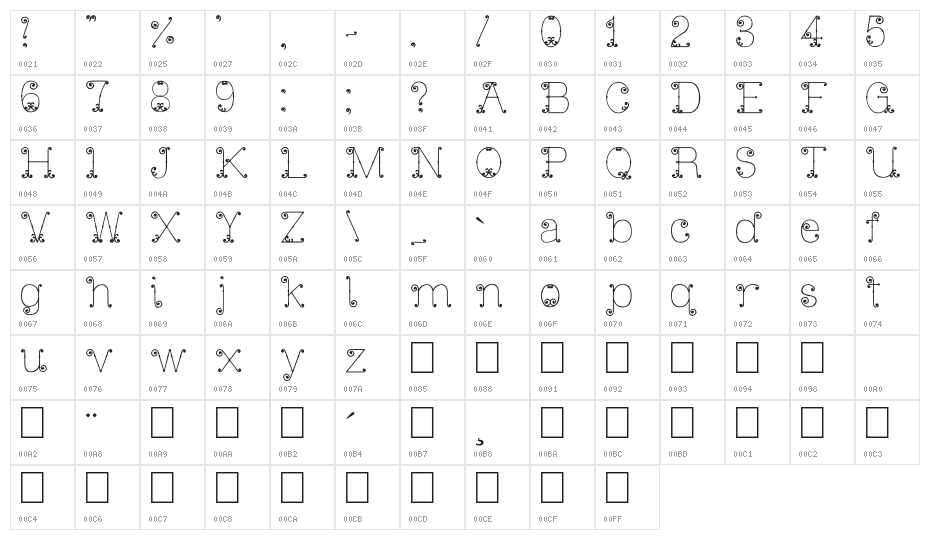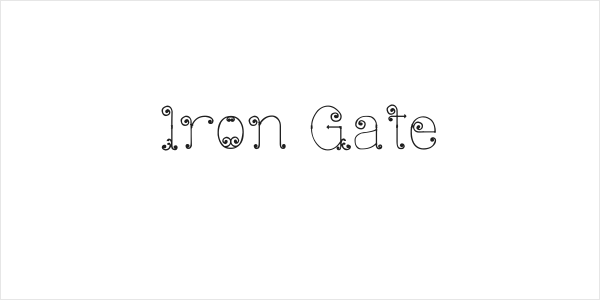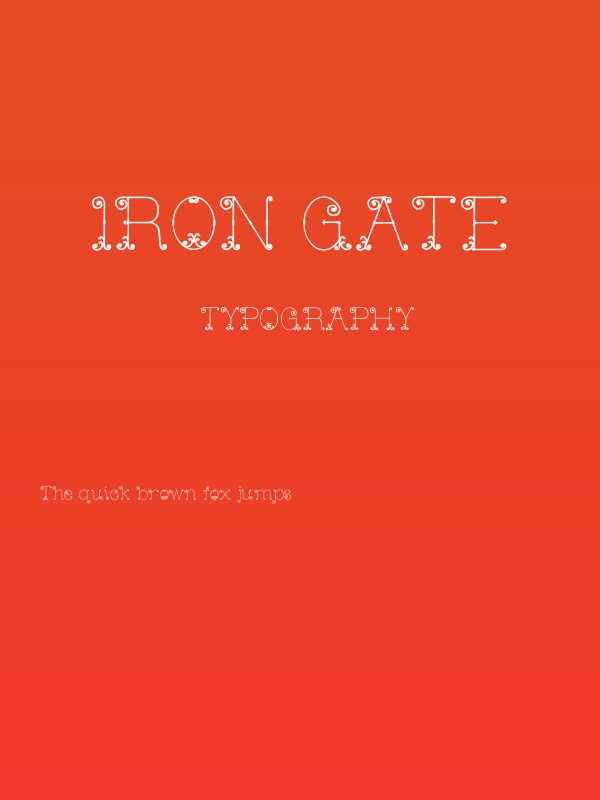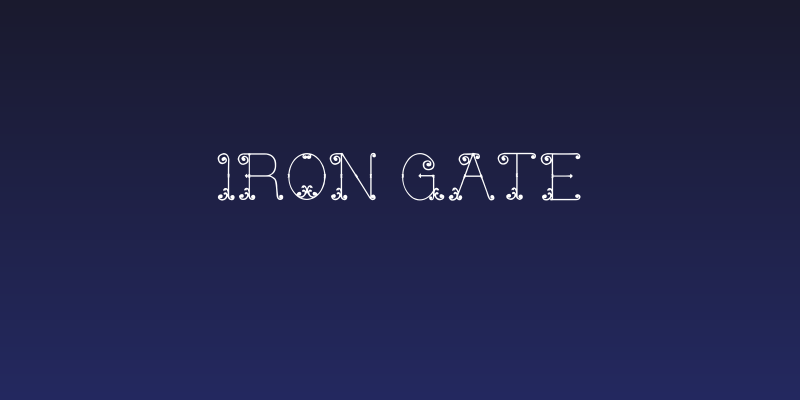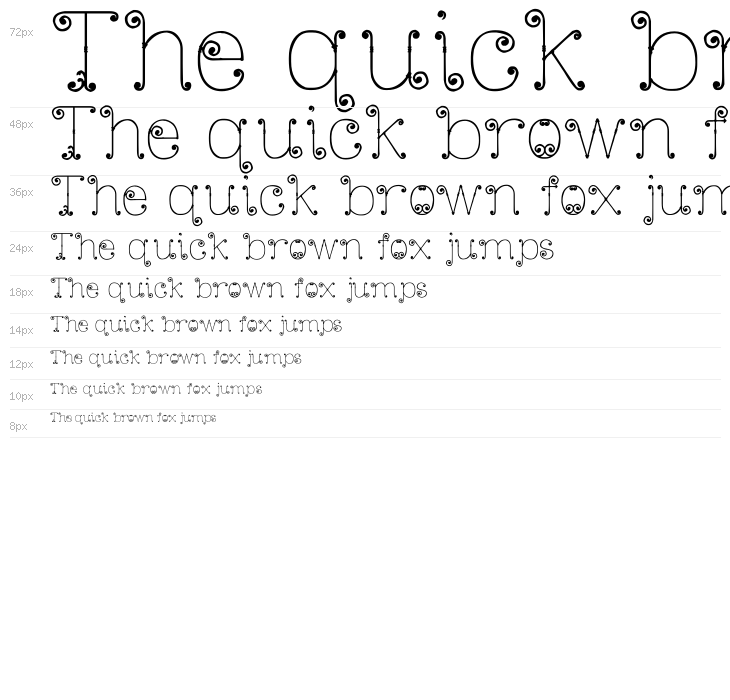
Iron Gate Font
| Caso d'uso | Headlines, Logos, Invitations |
| Progetti proposti | Ideal for wedding invitations, greeting cards, artistic posters, and branding that requires a touch of elegance and creativity. |